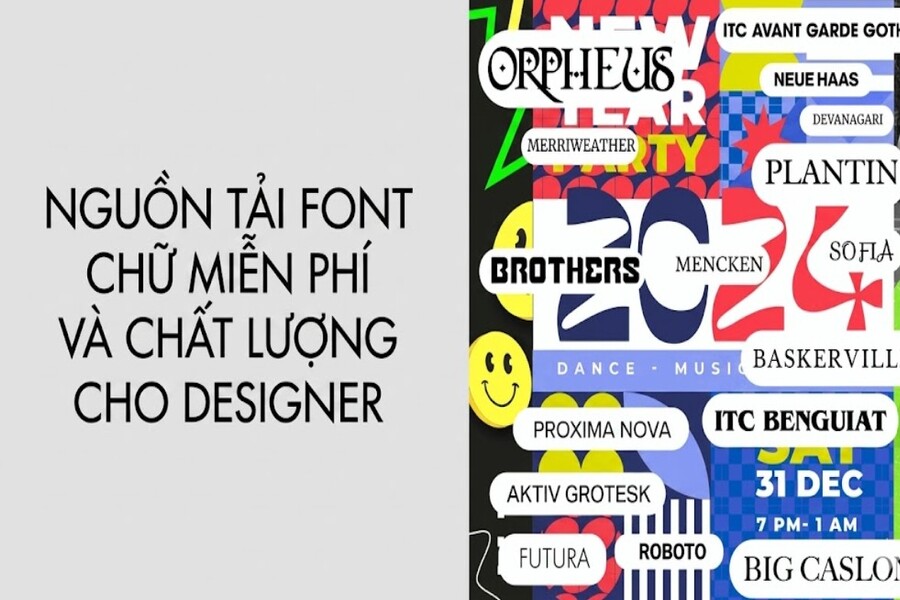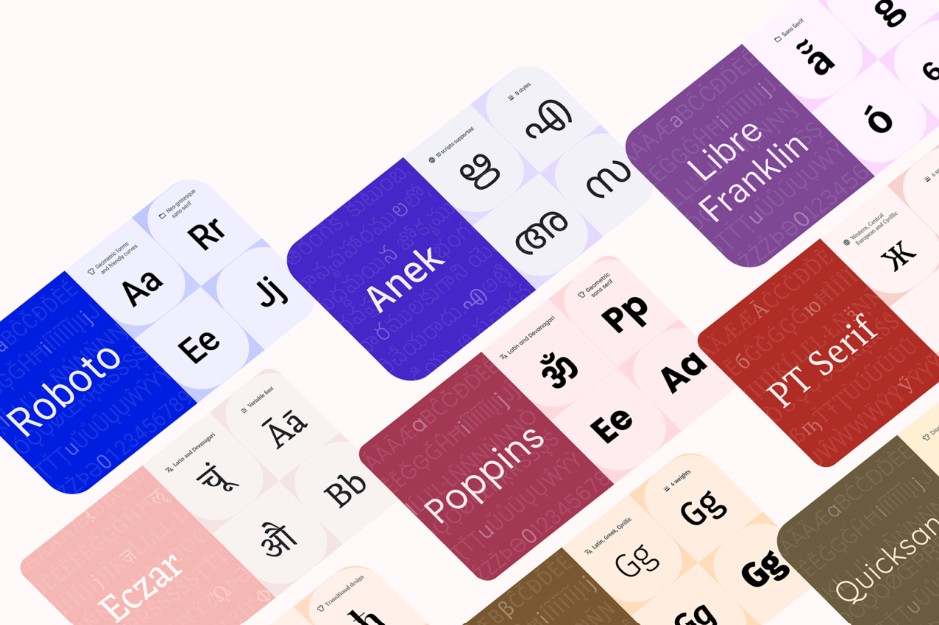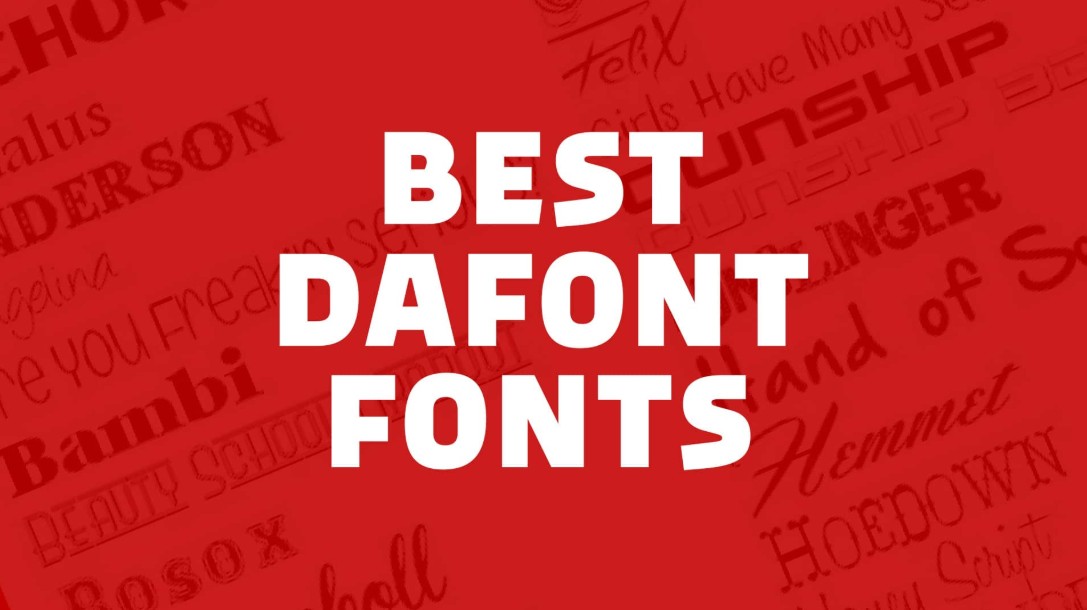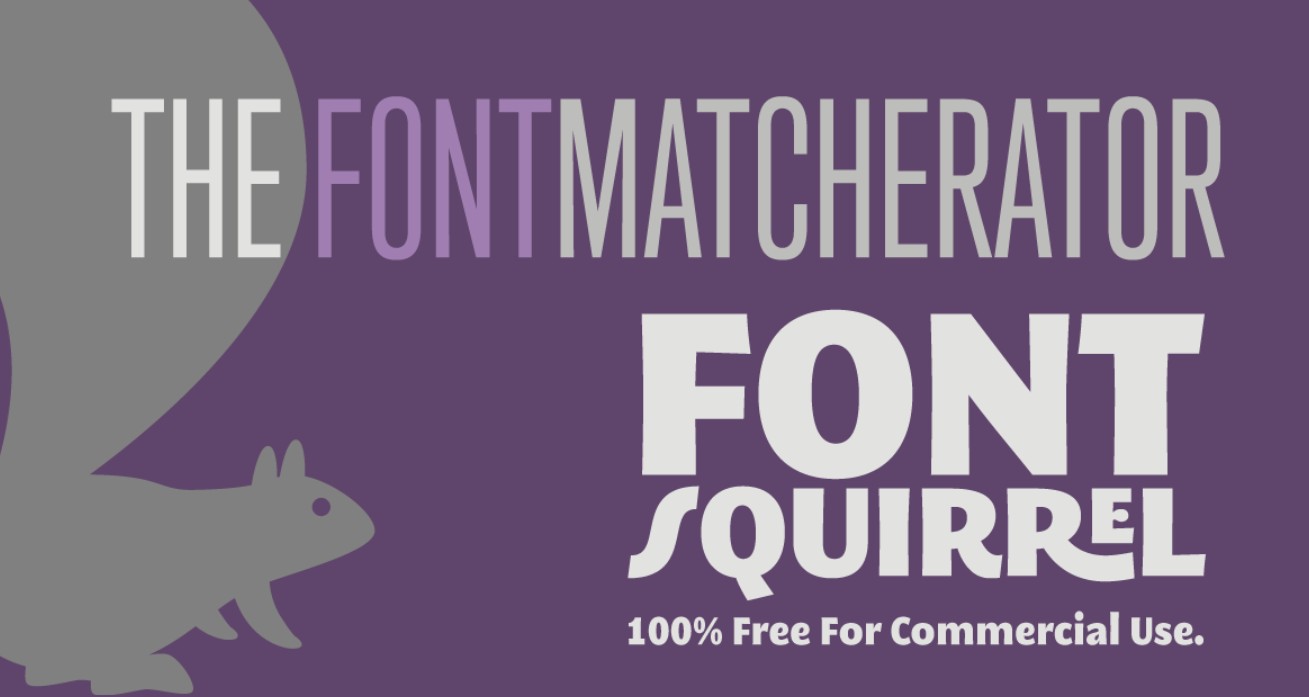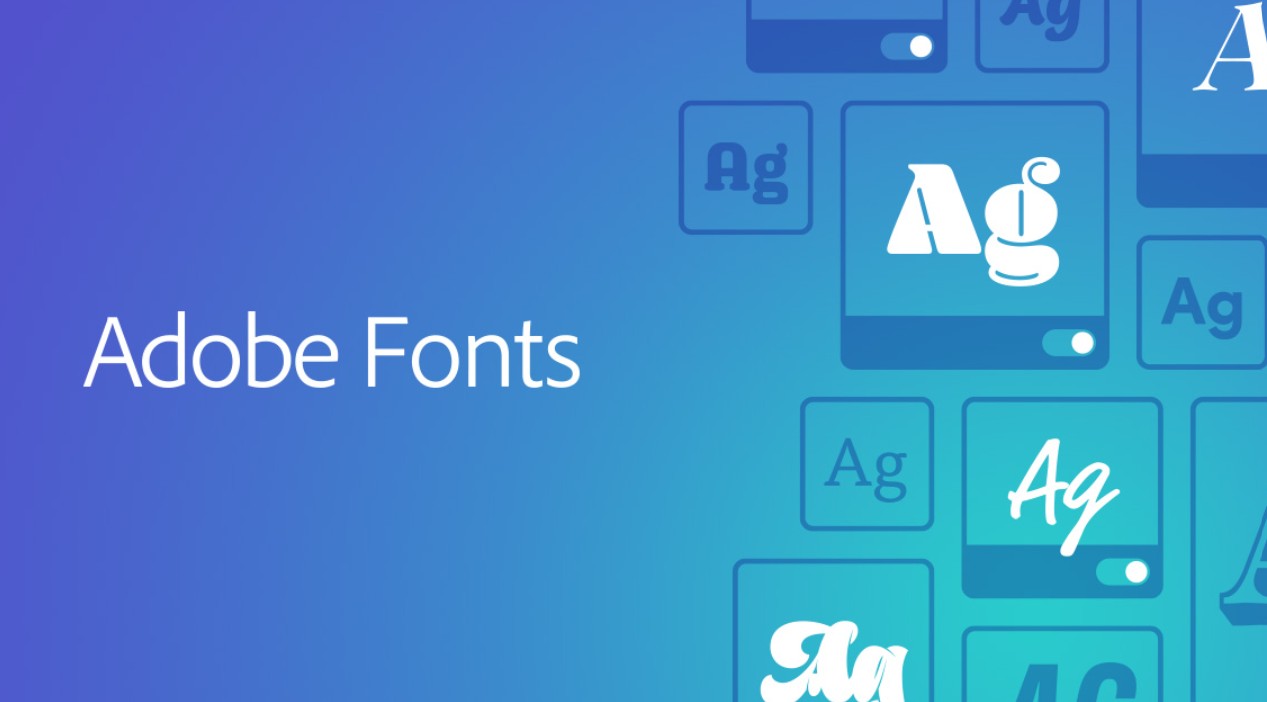
Nguồn Tải Font Chữ Miễn Phí Và Chất Lượng Cho Designer
Font chữ là yếu tố quan trọng giúp nâng cao chất lượng và tính thẩm mỹ trong thiết kế. Tuy nhiên, việc tìm kiếm nguồn font miễn phí vừa đẹp vừa an toàn không phải lúc nào cũng dễ dàng.
Trong thiết kế đồ họa hiện đại, font chữ không chỉ là công cụ hiển thị văn bản mà còn là yếu tố quan trọng góp phần định hình phong cách và cá tính của sản phẩm. Một thiết kế đẹp không thể thiếu sự kết hợp hài hòa giữa hình ảnh, màu sắc và typography. Đặc biệt khi làm việc với Adobe Photoshop, việc sở hữu thư viện font đa dạng và chất lượng sẽ giúp designer linh hoạt hơn trong sáng tạo, từ đó tạo ra những sản phẩm ấn tượng và chuyên nghiệp.
Tuy nhiên, không phải ai cũng biết cách tìm kiếm nguồn font uy tín hoặc sử dụng font sao cho hiệu quả. Việc tải font từ những nguồn không rõ ràng có thể gây ra rủi ro về bản quyền hoặc bảo mật. Đồng thời, nếu không biết cách sử dụng font hợp lý, thiết kế rất dễ trở nên rối mắt hoặc thiếu tính thẩm mỹ. Vì vậy, trong bài viết này, SaDesign sẽ giúp bạn hiểu rõ cách sử dụng font chữ hiệu quả trong Photoshop, đồng thời gợi ý những nguồn tải font miễn phí và chất lượng để bạn nâng cấp thiết kế của mình.
1. Vai trò của font chữ trong thiết kế
Font chữ không chỉ đơn thuần là công cụ hiển thị nội dung mà còn là yếu tố cốt lõi quyết định cách người xem cảm nhận một thiết kế. Trong nhiều trường hợp, typography chính là điểm chạm đầu tiên giữa sản phẩm và người dùng, vì vậy việc lựa chọn font phù hợp sẽ giúp truyền tải thông điệp nhanh chóng, rõ ràng và hiệu quả hơn. Một font chữ tốt có thể tạo điểm nhấn mạnh mẽ, dẫn dắt ánh nhìn và giúp người xem ghi nhớ nội dung lâu hơn.
Khi làm việc với Adobe Photoshop, font chữ còn ảnh hưởng trực tiếp đến bố cục và sự cân bằng thị giác. Nếu sử dụng font không phù hợp về tỷ lệ, độ dày hoặc khoảng cách, thiết kế có thể trở nên rối mắt, thiếu chuyên nghiệp và khó đọc. Ngược lại, khi lựa chọn đúng font, bạn có thể nâng tầm toàn bộ sản phẩm mà không cần thay đổi quá nhiều yếu tố khác như màu sắc hay hình ảnh.
Ngoài ra, font chữ còn đóng vai trò quan trọng trong việc xây dựng nhận diện thương hiệu. Mỗi kiểu chữ mang một “cá tính” riêng, từ sang trọng, hiện đại đến trẻ trung hoặc phá cách. Việc sử dụng font nhất quán trong các ấn phẩm sẽ giúp thương hiệu trở nên dễ nhận diện và tạo dấu ấn rõ ràng trong mắt người dùng. Chính vì vậy, font chữ không chỉ là chi tiết nhỏ mà là một phần chiến lược trong thiết kế chuyên nghiệp.
2. Các mẹo sử dụng font chữ đẹp trong Photoshop
2.1 Sử dụng đúng loại font cho mục đích thiết kế
Mỗi loại font chữ đều mang một phong cách và cảm xúc riêng, vì vậy việc lựa chọn đúng loại font cho từng mục đích thiết kế là yếu tố quan trọng hàng đầu. Font serif thường mang lại cảm giác truyền thống, đáng tin cậy và phù hợp với các ấn phẩm mang tính trang trọng như brochure, báo chí hoặc thương hiệu cao cấp. Trong khi đó, font sans-serif lại thể hiện sự hiện đại, tối giản và dễ đọc, rất phù hợp cho thiết kế số, website hoặc nội dung mạng xã hội.
Font script thường được sử dụng trong các thiết kế mang tính cá nhân hóa hoặc nghệ thuật như thiệp cưới, poster sáng tạo, trong khi display font lại đóng vai trò tạo điểm nhấn mạnh mẽ cho tiêu đề hoặc slogan. Khi làm việc trong Adobe Photoshop, việc xác định rõ mục tiêu thiết kế ngay từ đầu sẽ giúp bạn lựa chọn font chính xác, đảm bảo sự nhất quán và tăng hiệu quả truyền tải thông điệp.
2.2 Kết hợp các font chữ một cách hài hòa
Kết hợp font là một kỹ năng quan trọng giúp thiết kế trở nên sinh động và chuyên nghiệp hơn. Tuy nhiên, nếu sử dụng quá nhiều font hoặc chọn sai cách kết hợp, bố cục sẽ trở nên rối và thiếu điểm nhấn. Nguyên tắc phổ biến là chỉ nên sử dụng từ hai đến ba font trong một thiết kế để đảm bảo sự cân bằng.
Một cách hiệu quả là sử dụng một font chính cho tiêu đề và một font phụ cho nội dung, từ đó tạo sự phân cấp rõ ràng. Ngoài ra, nên ưu tiên kết hợp các font có sự tương phản nhưng vẫn bổ trợ cho nhau, chẳng hạn như một font sans-serif hiện đại đi cùng một font script mềm mại hoặc serif kết hợp với display để tạo chiều sâu thị giác. Sự hài hòa trong cách phối font sẽ giúp thiết kế trở nên chuyên nghiệp và dễ tiếp cận hơn.
2.3 Điều chỉnh khoảng cách chữ và dòng
Khoảng cách chữ (tracking), khoảng cách giữa các ký tự (kerning) và khoảng cách dòng (leading) là những yếu tố kỹ thuật quan trọng nhưng thường bị bỏ qua. Trên thực tế, đây lại là những yếu tố quyết định đến khả năng đọc và sự tinh tế của thiết kế.
Trong Adobe Photoshop, bạn có thể dễ dàng điều chỉnh các thông số này để phù hợp với từng bố cục cụ thể. Việc tăng hoặc giảm khoảng cách chữ giúp nội dung “thoáng” hơn hoặc “chặt” hơn tùy theo mục đích. Khoảng cách dòng hợp lý sẽ giúp người đọc theo dõi nội dung dễ dàng mà không bị mỏi mắt. Khi được tinh chỉnh đúng cách, những chi tiết nhỏ này sẽ tạo nên sự khác biệt lớn về mặt thẩm mỹ.